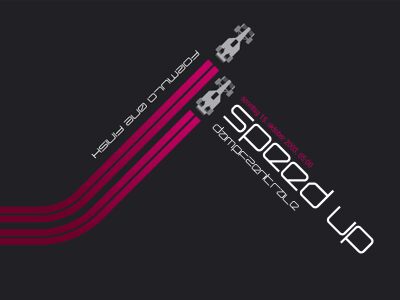
Querround Regular od Onezero je bezplatné, futuristické display písmo se klidným, modulárním rytmem. Písmena působí, jako by byla vykreslena ze zaoblených obdélníků a čistých křivek; kombinují otevřené geometrické tvary s lehce hravou technickou náladou, díky níž font nepůsobí chladně.
Přirozeně zapadne do brandingu založeného na rozhraních, grafik pro elektronickou hudbu, titulků na plakátech, obalů i krátkých logotypů, kde tento „vypolstrovaný“ sci-fi tvar může udávat tón. Jako bezplatné písmo se skvěle hodí také pro titulní karty, názvy aplikací a krátké řádky textu, zejména pokud hledáte zaoblenou geometrii, která působí lidštěji než tvrdé techno písmo.